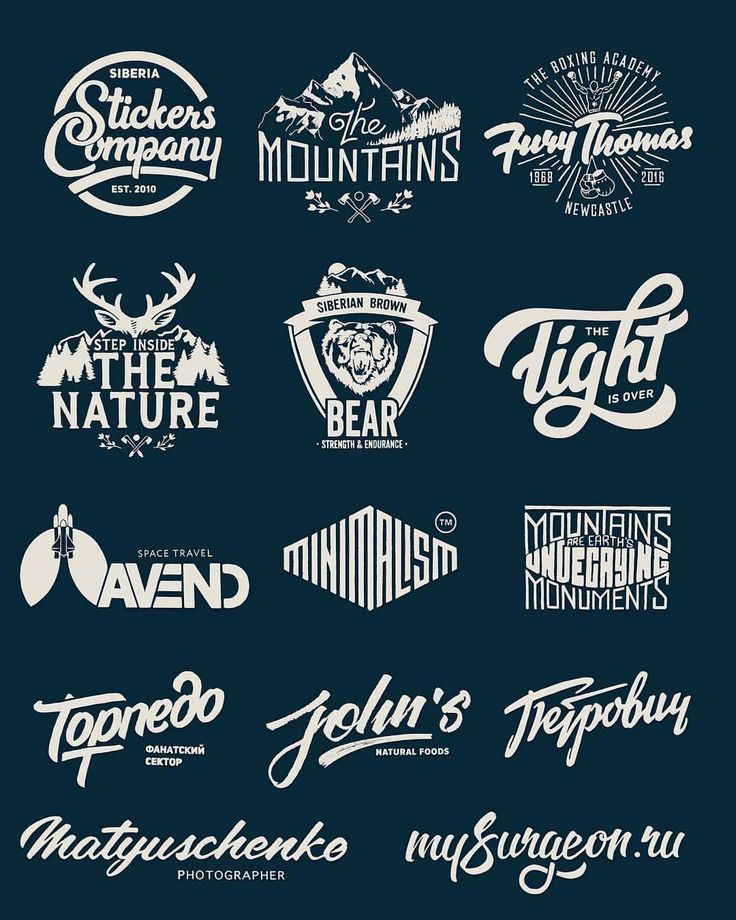
Лучшие шрифты для логотипа
Говорят, что компания без логотипа — это как человек без лица. Иногда это просто графический символ. В других случаях это сочетание графики и текста. При этом правильный шрифт иногда может быть одним из решающих элементов брендинга, потому что то, по чему мы узнаем компанию или бренд, обычно является его логотипом.
Каким должен быть идеальный шрифт для дизайна логотипа вашего бренда? На этот вопрос трудно ответить однозначно. Выбор зависит от концепции и того, что вы хотите передать. То, что распространено и модно, не всегда должно работать. Любой человек, разбирающийся в типографике, знает это. Что же должно отличать современный шрифт для логотипа с первого взгляда? Прежде всего, это шрифт, соответствующий характеру бренда (например, элегантные изгибы, толстые прямые линии, слова, написанные только заглавными буквами). По этой причине кране важно подобрать подходящий.
Что такое логотип
Логотип — это уникальный графический знак, символ компании, который является частью ее визуальной идентичности. Главная задача логотипа — отличать компанию от конкурентов и легко запоминаться потребителям. Вы наверняка знакомы с логотипами Nike, CocaCola или McDonalds — это примеры идеального логотипа.
Лучшие шрифты для логотипа
Ниже вы найдете по 8 предложений бесплатных и платных шрифтов для использования в ваших проектах. Здесь кратко описаны наиболее интересные из них.
Этот шрифт с засечками использовался такими брендами, как Calvin Klein (наряду с Futura) и Vogue. Шрифт выглядит эстетично, контрастные толстые и тонкие штрихи и плоские, бесшовные засечки добавляют выразительности.
Cloud Sans. Бесплатное шрифтовое предложение в шрифте Sans Serif поставляется в пяти разновидностях (Bold и Light доступны бесплатно).
Символы могут быть написаны курсивом. -
Один из самых популярных шрифтов, используемых при разработке логотипов. Четкий, стильный и доступен (как и другие бесплатные) в базе данных Google Fonts. Хотя он подходит для многих брендов, он не подойдет для каждого проекта (например, типографика, ориентированная на элегантность или с преимущественно письменными символами).
Шрифт, обозначающий самое солнечное время года. Доступны бесплатно в 18 стилях.
Шрифт назван в честь одного из районов Буэнос-Айреса. Подходит под простую, выразительную типографику.
Простой шрифт, используемый в дизайне и печати, который представляет собой геометрический шрифт без засечек. Доступны бесплатно в 18 стилях.
Неогротескный шрифт, такой же популярный, как Helvetica и Arial, используемый в рекламе или печатных рекламных материалах, таких как брошюры, флаеры и т.
д. Шрифт гарантирует чистый, простой дизайн. -
Roboto Slab. Этот шрифт является эквивалентом Roboto с засечками. Оба шрифта можно успешно комбинировать. Четкие геометрические формы Roboto Slab подходят под типографику сильных, специфических брендов.
Иногда бренду, который хочет выделиться, требуется нестандартное решение. В таких случаях бесплатного и общепринятого недостаточно, необходимо инвестировать. Именно для этого были созданы шрифты премиум-класса.
Тщательно обдумайте свой выбор, прежде чем принять решение. Например, шрифт Fonjava или OGG идеально подходит для элегантных винтажных и других дизайнов. Его дизайн гарантирует высокую эстетику, способную вдохновить такие материалы, как плакаты, визитные карточки или приглашения. Нью-Йорк Gotham, с другой стороны, резонирует с бизнесом, ориентированным на построение прочных отношений и доверия.
Среди шрифтов премиум-класса стоит отметить следующие:
Avenir;
Dry Brush;
Fonjava;
Futura;
Gotham;
Lydian;
OGG;
Zelda.
Только вам решать какой из вариантов выбрать.
Каждый, кому когда-либо приходилось выбирать шрифт, например, для веб-сайта, знает, как легко запутаться. Количество шрифтов, доступных в различных стилях, может вскружить голову. Особенно для тех, у кого нет опыта работы в сфере дизайна. Даже у опытного дизайнера могут возникнуть проблемы с выбором. Поэтому, прежде чем разрабатывать логотип и выбирать шрифт, дизайнер должен подумать о том, что он хочет передать. Еще одним соображением будет использование бесплатных или платных шрифтов.